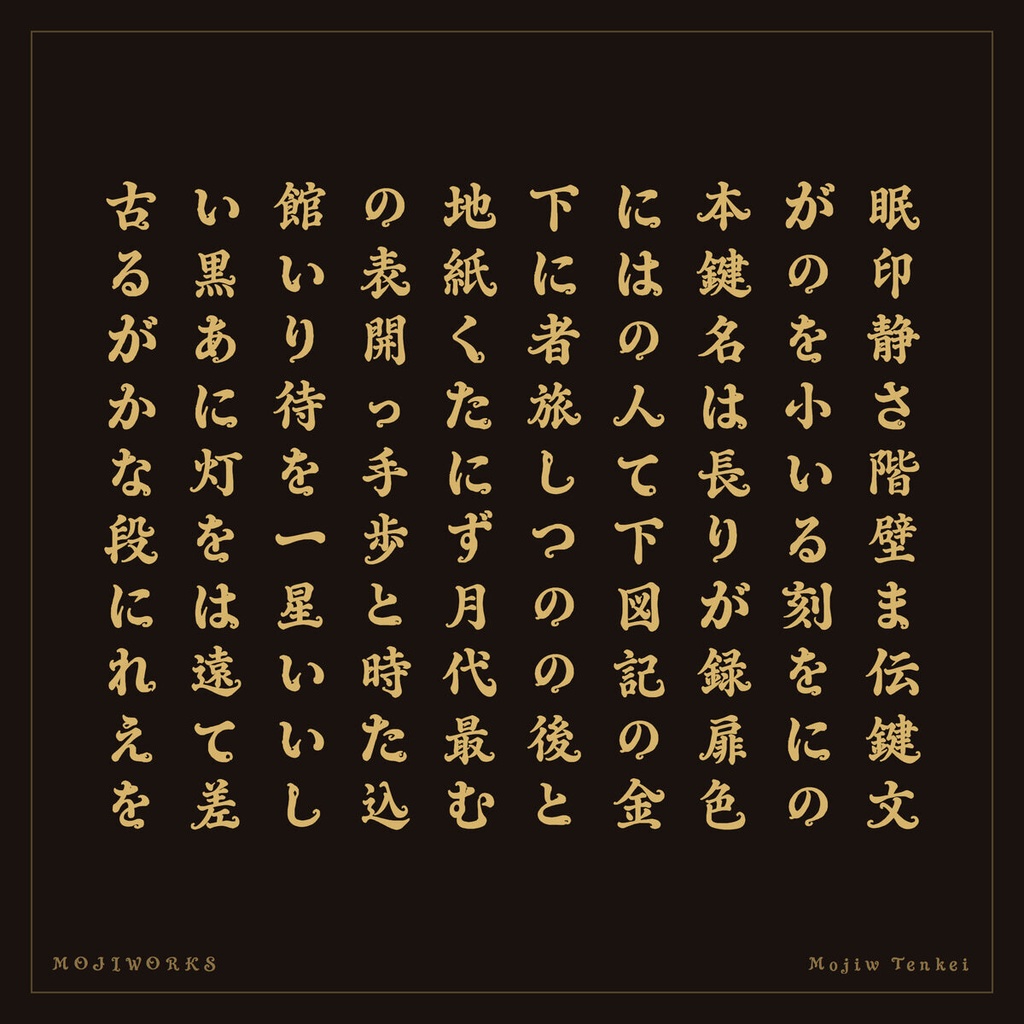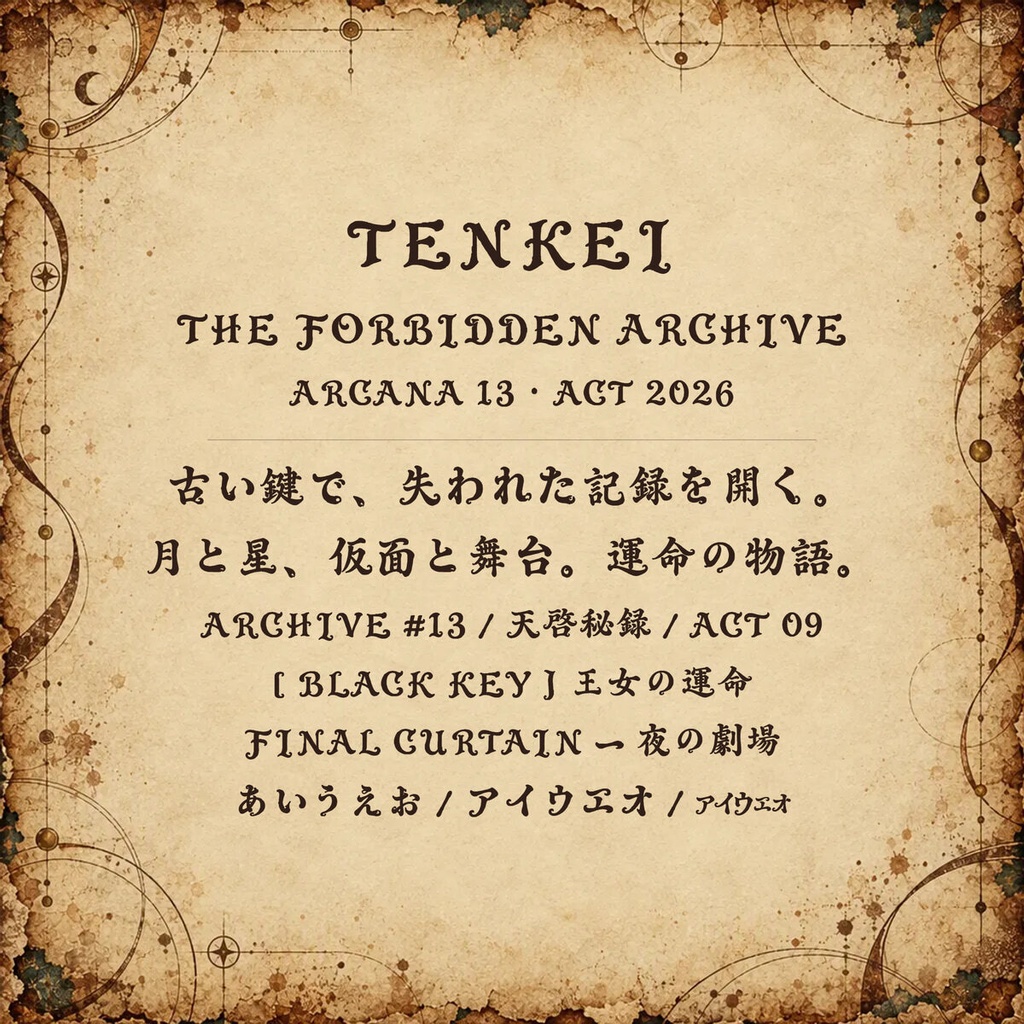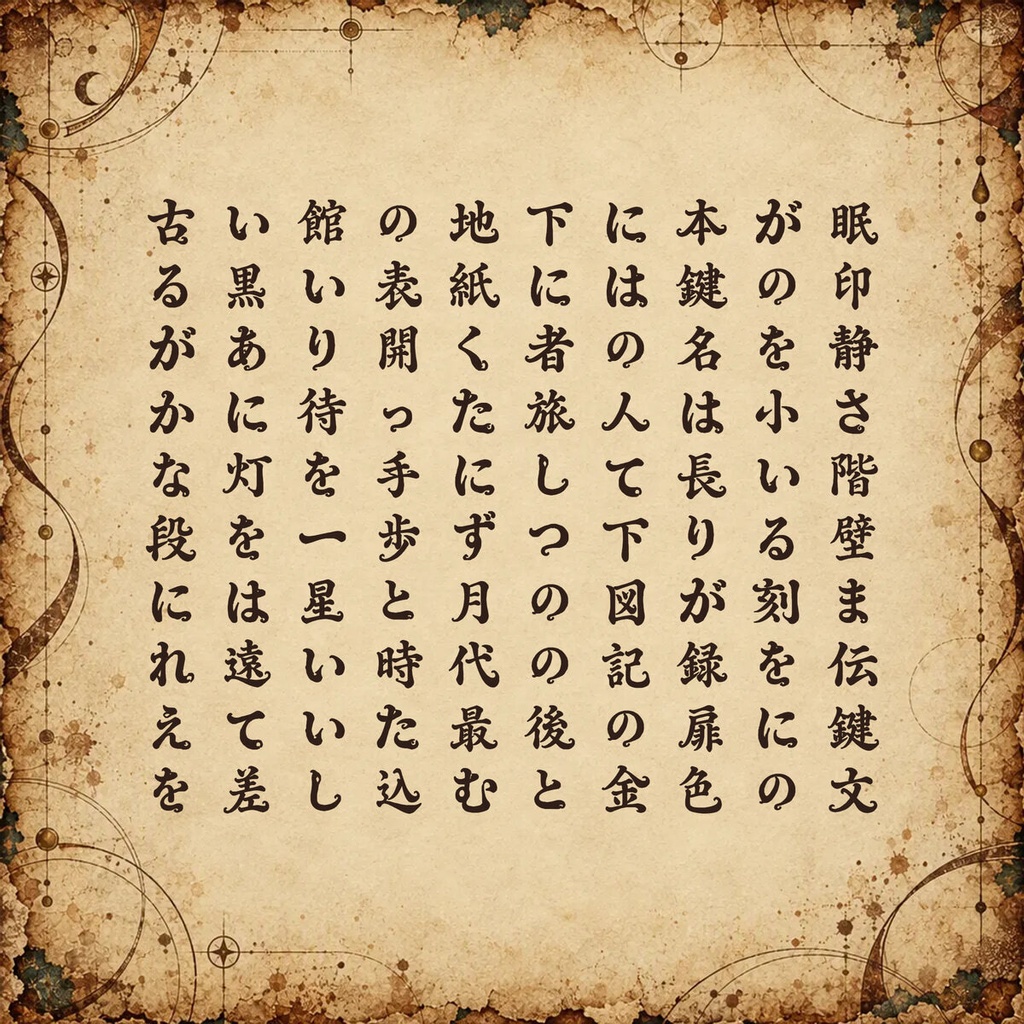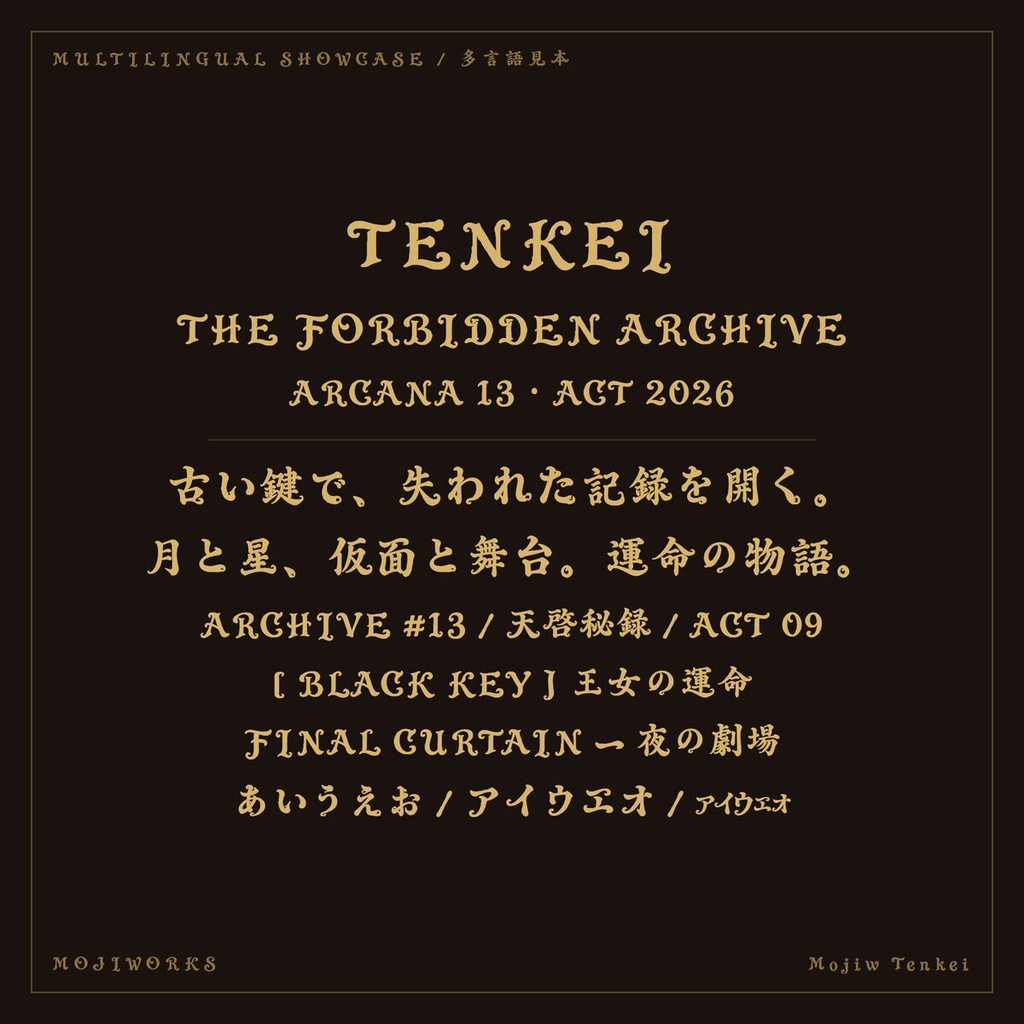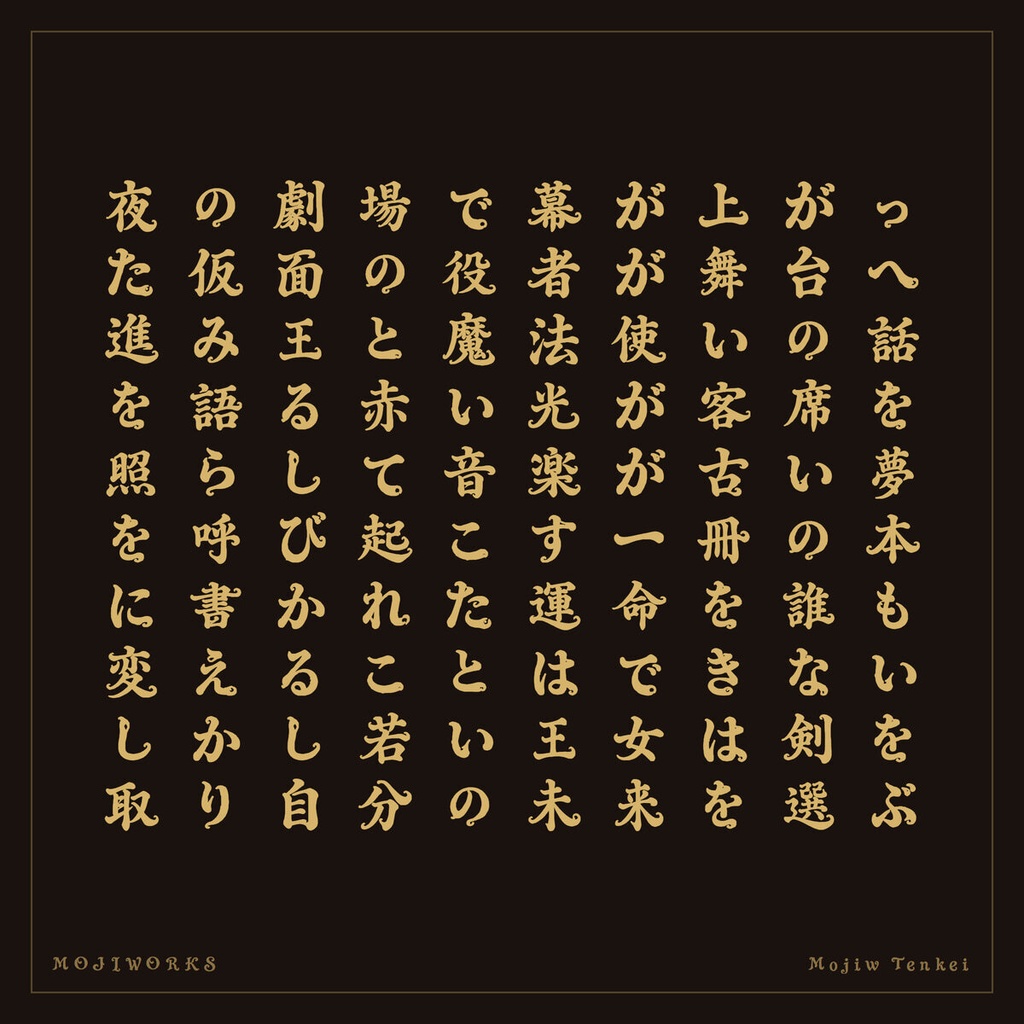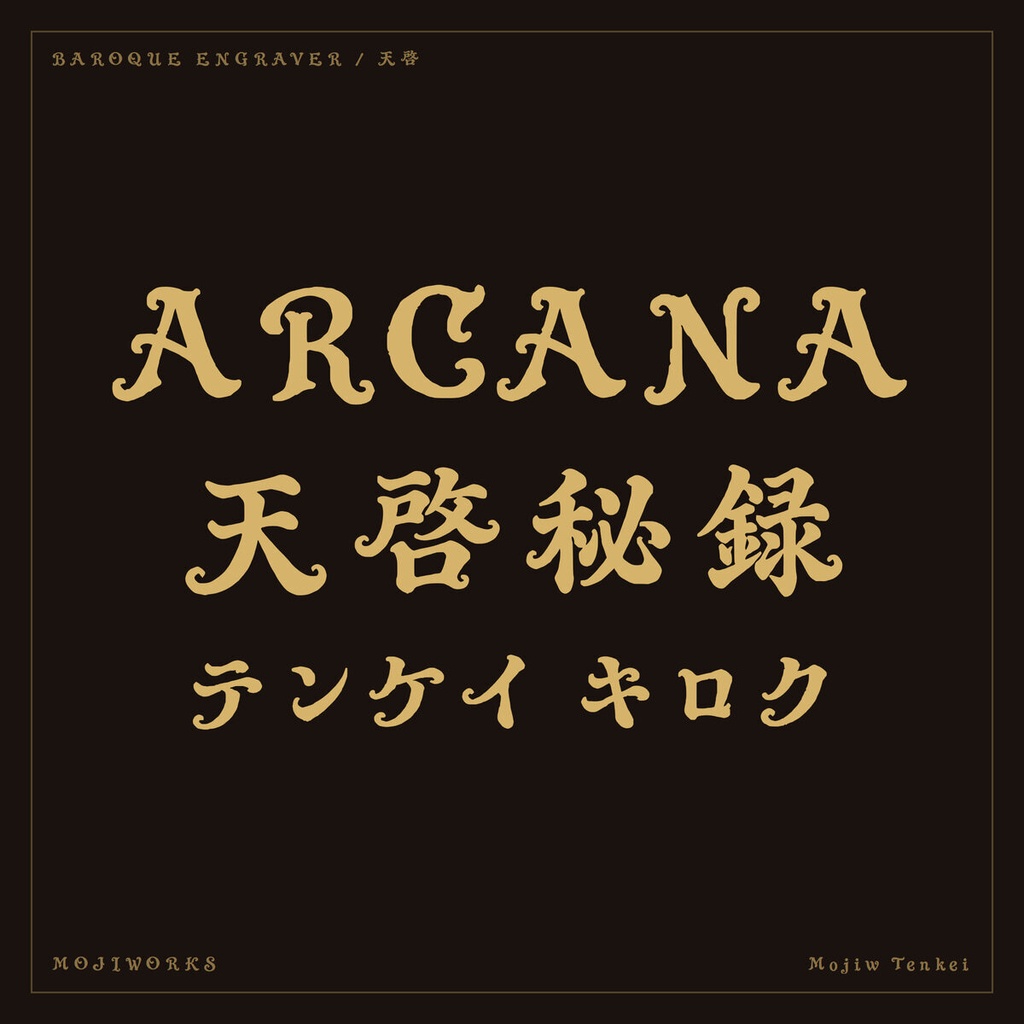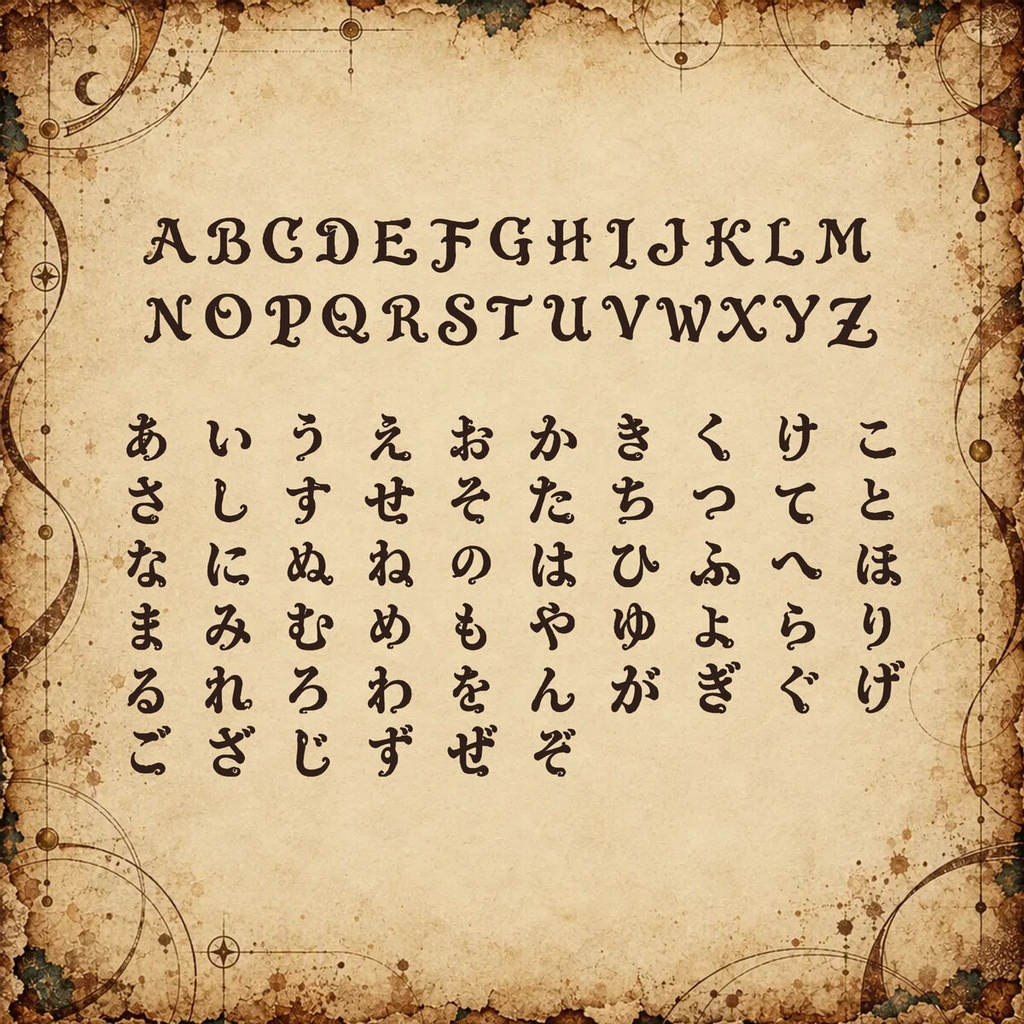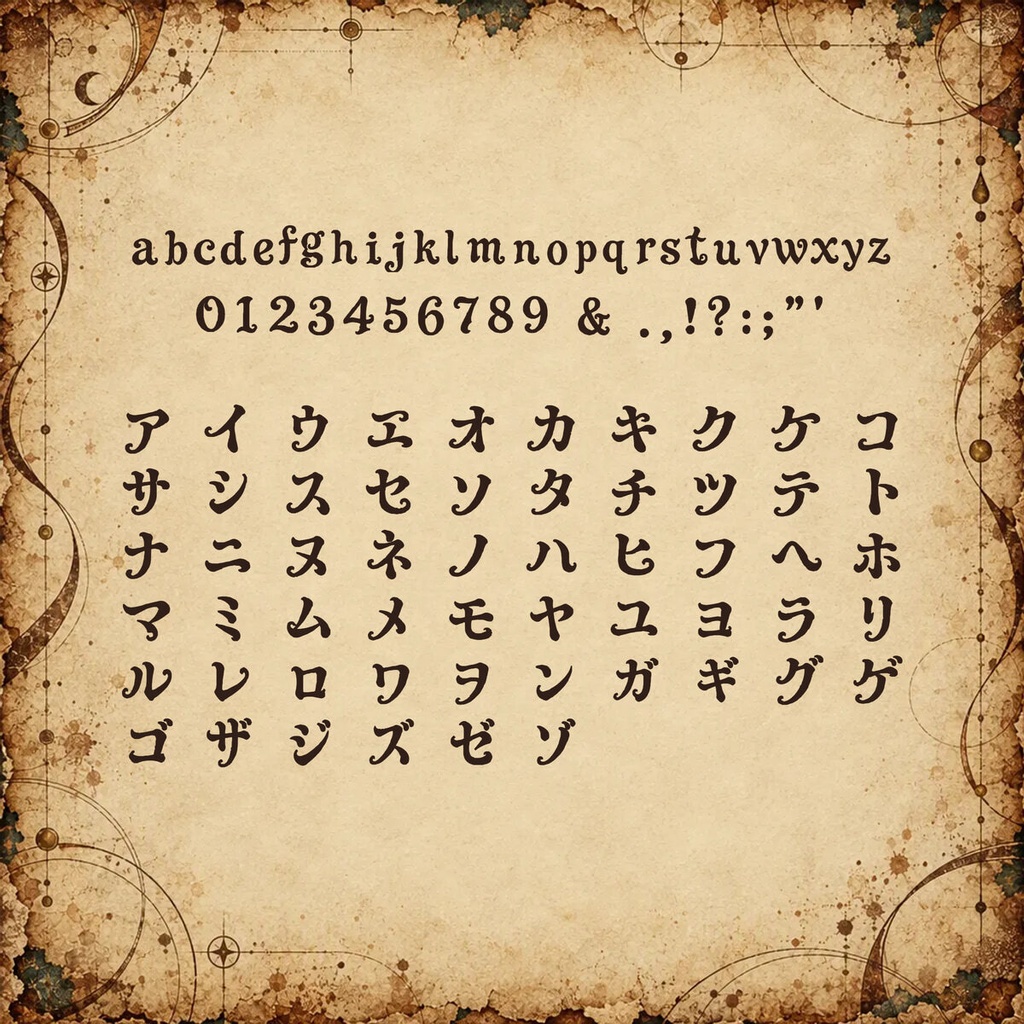
天啓 Tenkei【フォント】 — 蛇行するバロック彫刻書体|常用漢字2,136字
黒いリボンのような曲線と鍵穴を刻んだ、異端の彫刻書体です。 An eccentric baroque display face sculpted from serpentine black ribbons and keyhole apertures. 【用途 / Use】 ダークファンタジー / TRPG / 舞台 / 書籍 / ゲームタイトル For dark fantasy, TRPG, theatre, books, and game titles. 【常用漢字フル版 / Joyo Complete】 常用漢字2,136字を完全収録し、ラテン文字・ひらがな・カタカナ・記号を含む全2,437文字を収録しています。半角カナは収録していません。 Includes all 2,136 Joyo kanji and 2,437 characters total, including Latin, hiragana, katakana, and punctuation. Half-width kana are not included. 2437文字 / characters 【関連する収録版 / Other Edition】 ラテン文字・かな・記号を収録したスタンダード版もあります。 The Standard edition includes Latin, kana, and punctuation. ▶ スタンダード版 / Standard: https://mojiworks.booth.pm/items/8826761 【フォント仕様 / Specification】 バージョン / Version: 1.0.1 形式 / Format: TrueType (.ttf), Web (.woff2) 対応環境 / Platform: Windows, macOS, web browsers 収録字一覧 / Character list: CHARSET.txt 同梱 / Included: font files, README, LICENSE, character list, portfolio PDF, product previews. 【利用規約 / License Summary】 個人・商用利用可。1ライセンスは購入者1名に適用されます。 Personal and commercial use is permitted. One license covers one purchaser. 印刷・動画・ロゴ・グッズ等の静的成果物、および購入者が運営するサイトでの同梱WOFF2の利用が可能です。 Static output such as print, video, logos, and merchandise is permitted. The bundled WOFF2 may be used on a website owned or operated by the purchaser. ゲーム・アプリへの組み込みは、利用者が生のフォントを抽出できない形式に限ります。生のフォントを同梱する場合は別途ライセンスをご相談ください。 Game/app embedding requires protection against extraction of the raw font. Contact us for a separate runtime-embedding license when shipping raw font files. 標準ライセンスは1製品・1サイトあたり年間約100,000ユーザーまで。従業員50名超の組織を含む大規模利用は要相談。 Standard coverage is approximately 100,000 users per product/site/year. Larger use and organizations with more than 50 employees require an extended license. フォント本体の再配布・販売・貸与・変換・グリフ抽出・派生フォント制作・生成AI学習やスタイル参照は禁止です。 Redistribution, resale, lending, conversion, glyph extraction, derivative fonts, and generative-AI training or style reference are prohibited. 完全な利用条件は同梱の LICENSE.txt / LICENSE.jp.txt をご確認ください。 The bundled license files are authoritative; consult them for the complete terms. 【ほかのフォント・カスタム制作 / More Fonts and Custom Work】 フォント一覧、オーダーメイド書体、文字追加、拡張ライセンスのご相談はこちら。 Browse our catalog or contact us for custom typefaces, added characters, and extended licenses. https://mojiworks.booth.pm/